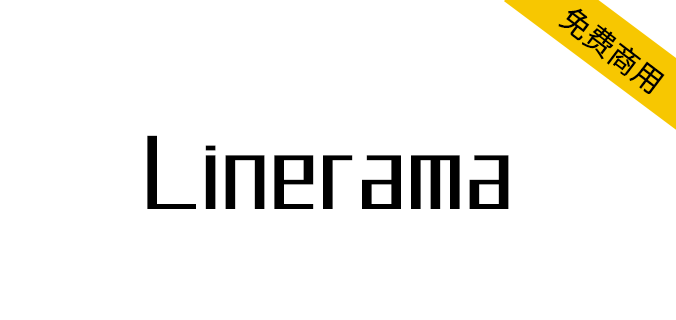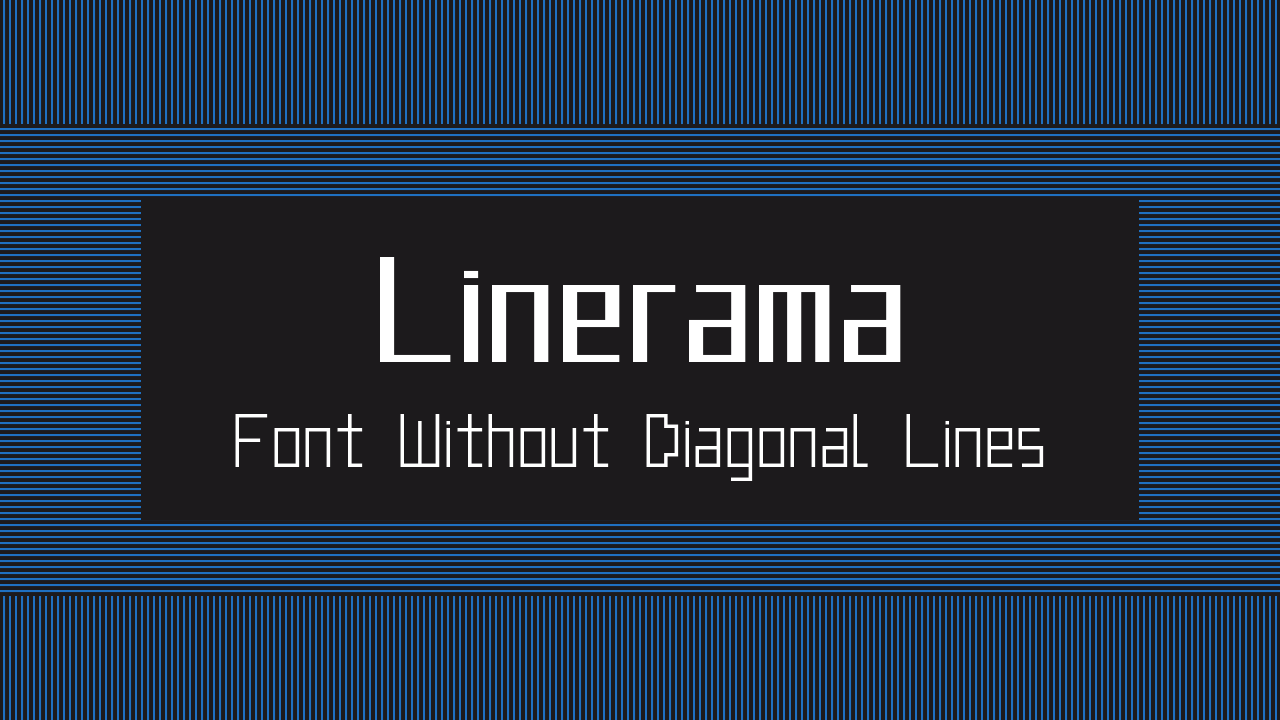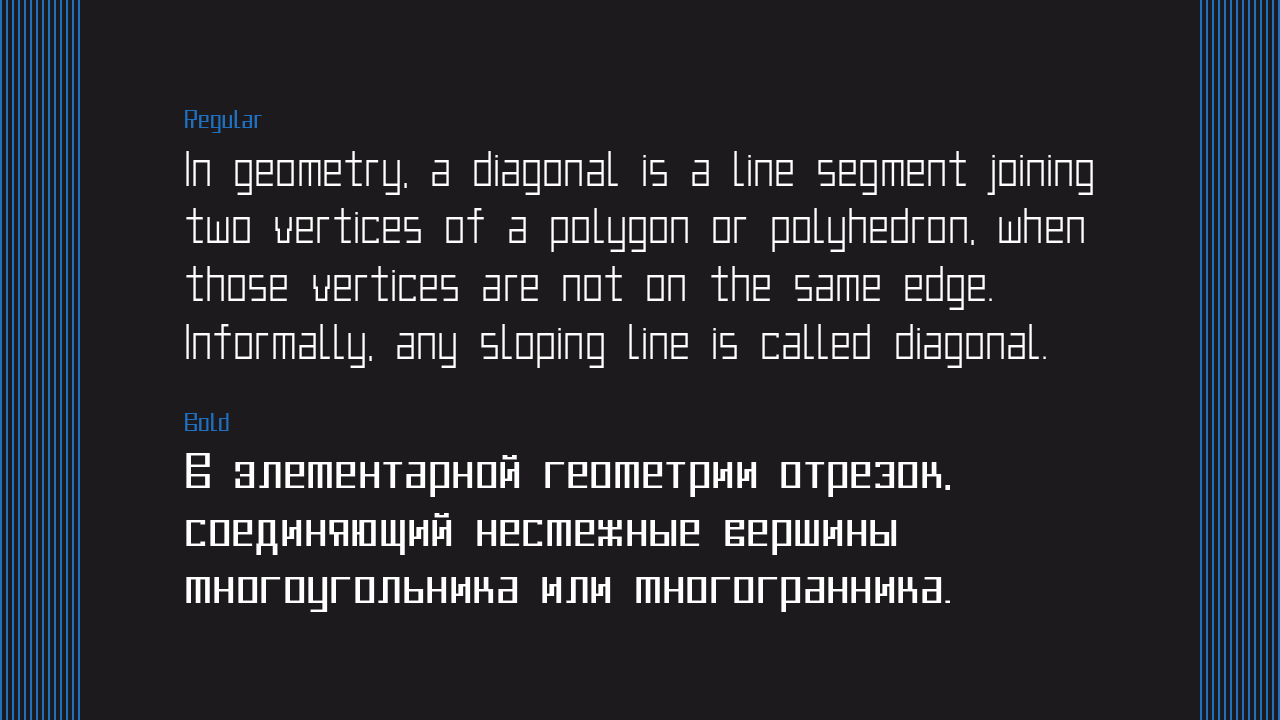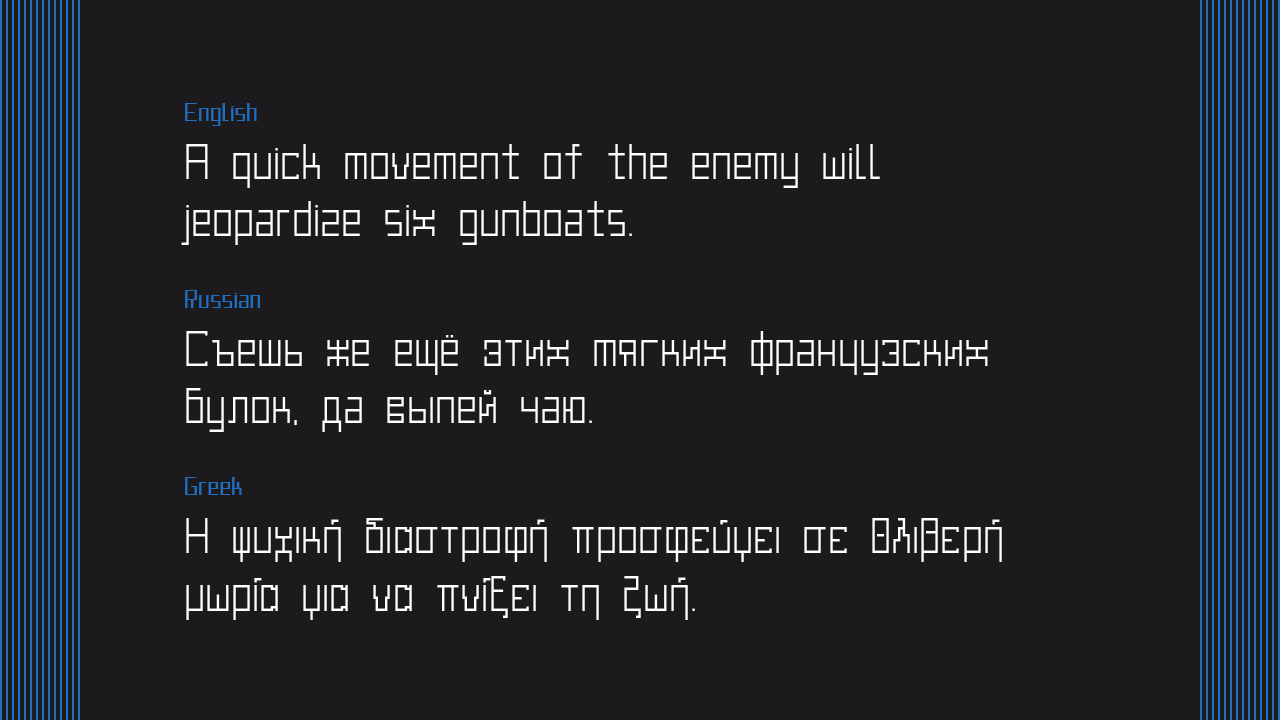
Linerama是一种没有对角线的免费英文字体,根据SIL OFL协议发布,包含 2 种样式(Regular、Bold)和 815 个字形。支持 92 种语言(Aghem, Aja, 阿尔巴尼亚语, Aromanian, Asturian, Azeri, Basaa, Bashkir, 白俄罗斯, 布列塔尼语, 保加利亚语, 加泰罗尼亚语, Central Yambasa, 中文(拼音), Chuvash, 克罗地亚语, 捷克语, Dagbani, 丹麦语, Duala, 荷兰语, 英语, 世界语,爱沙尼亚语、母羊语、Ewondo、芬兰语、Fon、法语、Fula、Gagauz、德语、希腊语、匈牙利语、冰岛语、伊博语、印度尼西亚语、爱尔兰语、意大利语、Jula、Kabyle、Kako、哈萨克语、Khoekhoe、Koyra Chiini、Koyraboro Senni、吉尔吉斯语、拉科塔语、拉丁语、拉脱维亚语、立陶宛语、利沃尼亚语、马赛语、马其顿语、马耳他语、马普顿贡语、蒙古语、Ngiemboon、恩贡巴语、北萨米语、挪威语、波兰语、葡萄牙语、里夫语、罗马尼亚语、俄语、苏格兰盖尔语、塞尔维亚语、塞尔维亚语、Shawiya、Shilha、斯科尔特萨米语、斯洛伐克语、斯洛文尼亚语、西班牙语、瑞典语、他加禄语、鞑靼语、特拉帕内克语、土耳其语、土库曼语、乌克兰语、乌兹别克语、瓦伊语、瓦尔瑟德语、威尔士语、西弗里斯兰语、扎尔马语、扎扎基语、祖鲁语。)